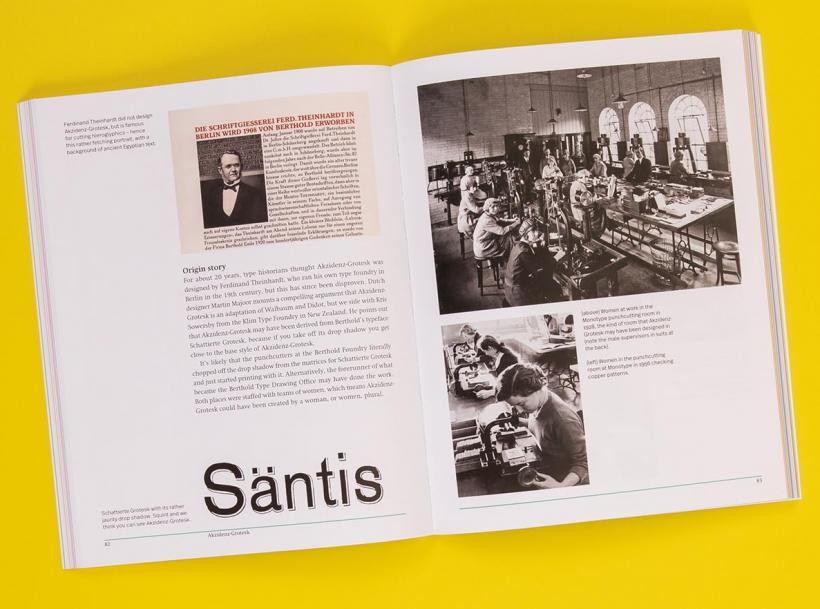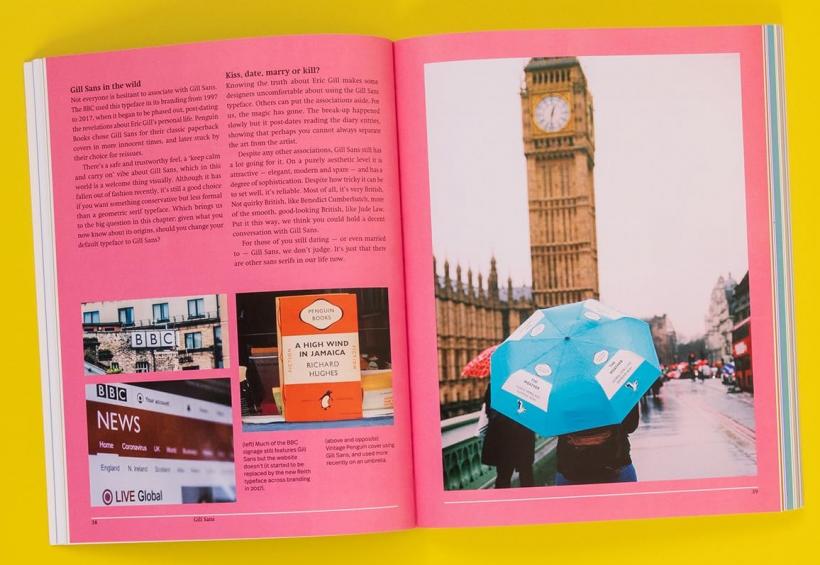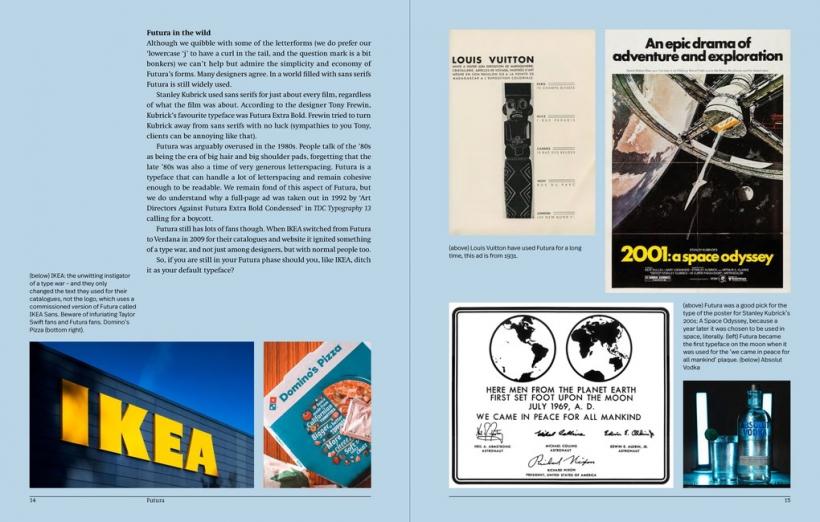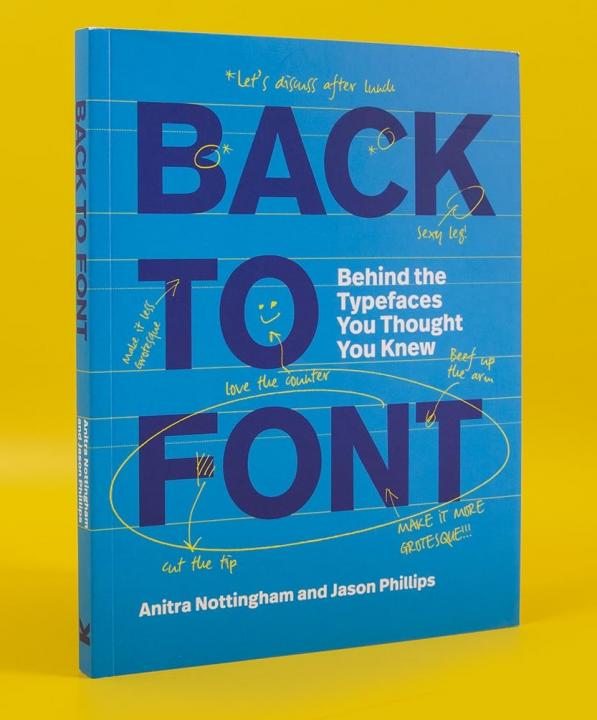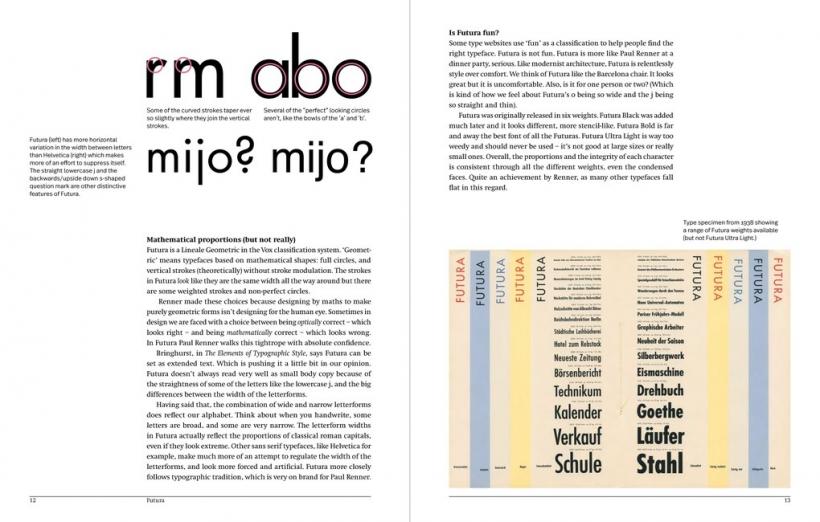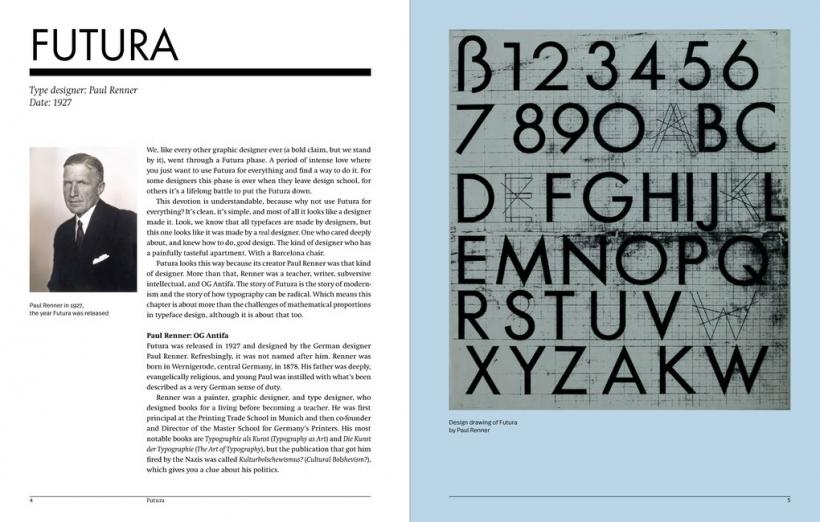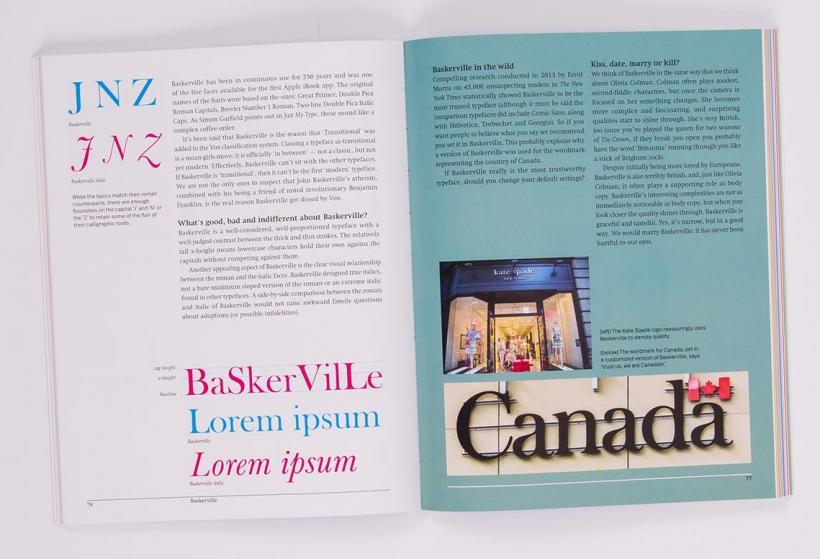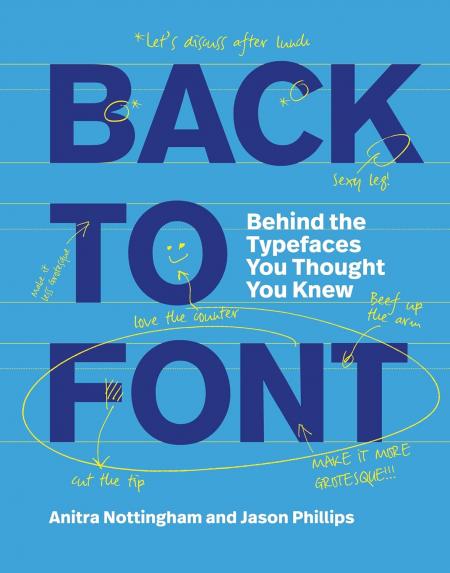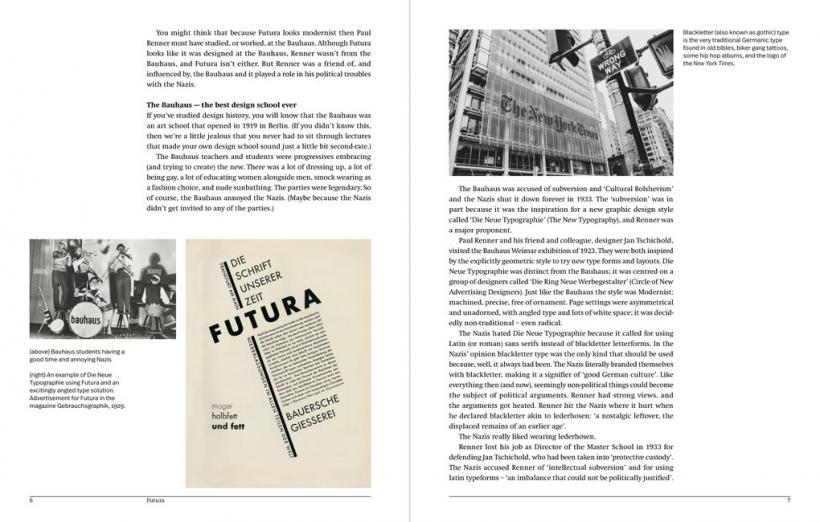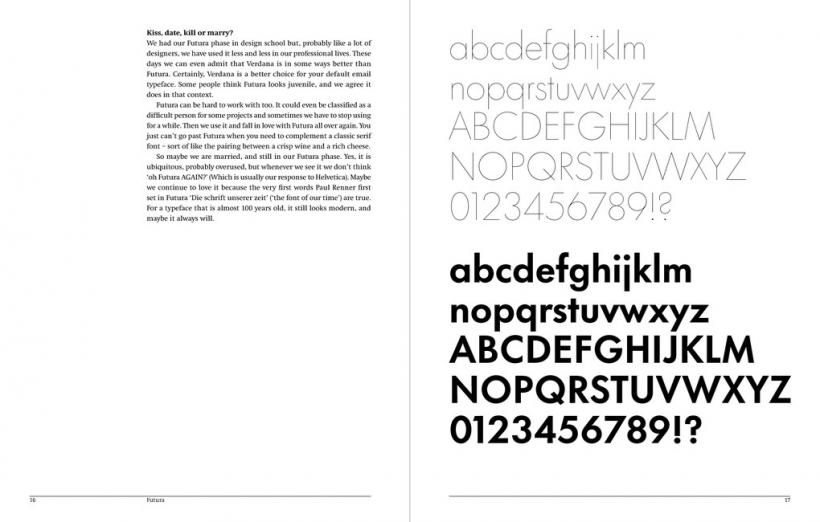
Back to Font: Behind the Typefaces You Thought You Knew
Увага: ця книга може змусити вас переосмислити налаштування шрифтів за замовчуванням.
Back to Font» розкриває секрети та життя 16 найвідоміших шрифтів. Вона відповідає на всілякі питання, які ви, можливо, ніколи раніше не задавали собі. Наприклад: хто були їхні «батьки» та де вони «народилися»? Що в них гарного та цікавого, а що ні? Як використовуються (і зловживають) ці шрифти, і де їх можна знайти «в дикій природі»? Найголовніше, що ці балакучі та висловлені думки допоможуть вам вирішити, чи варто цілувати, одружуватися чи вбивати кожен шрифт.
Хто б міг подумати, що шрифт може спровокувати такі суперечки? (Ми це зробили.)
У розділі:
Times New Roman / Gill Sans / Futura / Bodoni / Goudy / Baskerville / Akzidenz Grotesk /
Mrs Eaves / Trajan / Novarese / Bell Centennial / Foundry Sterling / Transport /
Zapf Dingbats / Univers / Papyrus
Про авторів:
Анітра Ноттінгем працювала дизайнером книг у видавництві Oxford University Press та Penguin Books, Australia. Протягом 13 років вона була онлайн-директором Школи графічного дизайну в Академії мистецтв Університету Сан-Франциско, де викладала типографіку та історію графічного дизайну. Зараз Анітра є провідним дизайнером навчання в онлайн-дизайні Мельбурнського університету, де, серед іншого, вона забезпечує правильне використання кінцевих тире командою з дизайну навчання.
Джейсон Філліпс розпочав свою кар'єру з дизайну банкнот, а потім перейшов до книжкового дизайну для Oxford University Press, Hardie Grant Books та низки інших австралійських та міжнародних видавництв. Він десять років викладав типографіку та редакційний дизайн у вищих навчальних закладах. Джейсон зараз працює над розробкою навчальних програм у секторі професійної підготовки, де його роль включає інформування зацікавлених сторін про те, що Arial — не їхній друг.